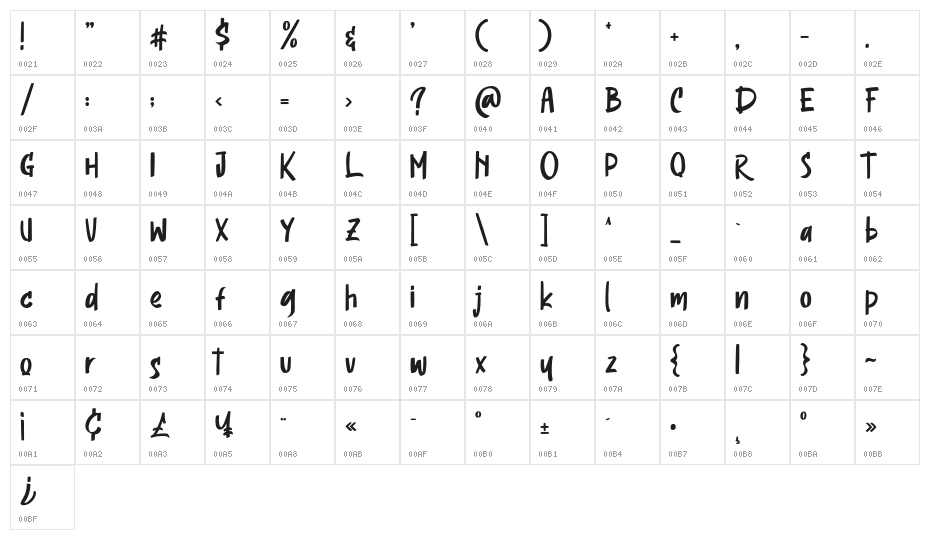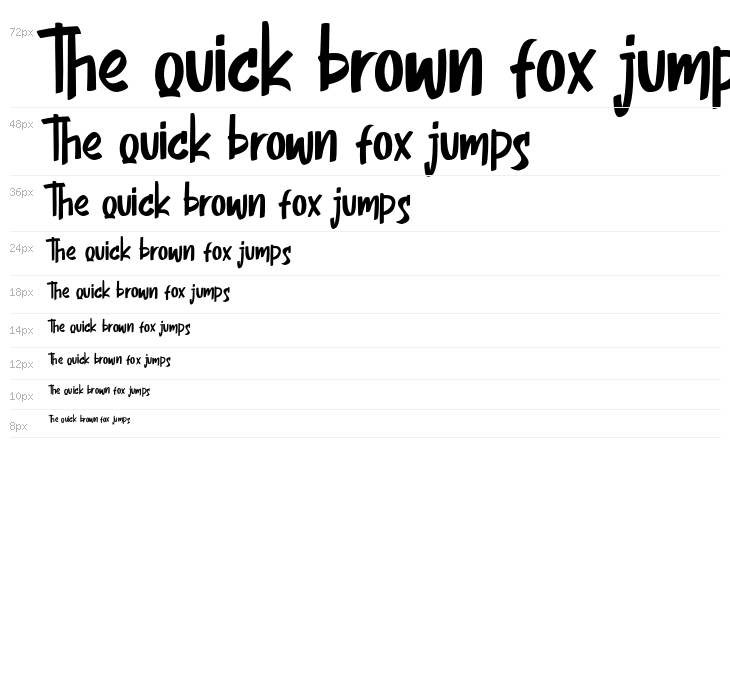
Headson Font
| Gesamtstil | Playful |
| Vorgeschlagene Projekte | Ideal for children's books, playful branding, casual invitations, and social media graphics. |